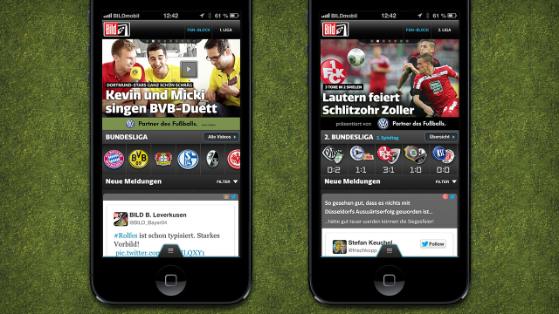
ich bin auf der Suche nach der Font, die die Bild in ihrer Bundesliga-App verwendet. Auffällig ist besonders das gebogene k/K.
Update: Ich habe inzwischen vom Bild-Art-Director die Antwort bekommen, dass es sich bei der Schrift um die Quatro Sans handelt.